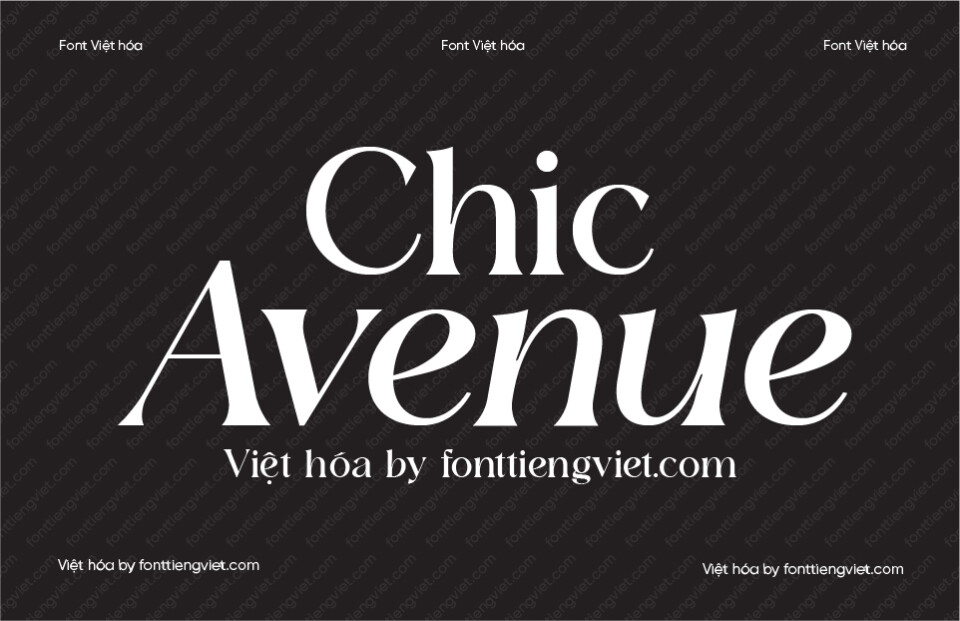
Font Việt hóa 1FTV VIP Chic Avenue
Font Việt hóa 1FTV VIP Chic Avenue – Bộ Font Chữ Sang Trọng Cho Thiết Kế Thời Thượng
Trong thế giới đồ họa hiện đại, việc tìm kiếm một bộ Font Việt hóa 1FTV VIP Chic Avenue hoàn chỉnh và tinh tế là nhu cầu thiết yếu của các nhà thiết kế. Đây là một phông chữ mang phong cách Serif cổ điển nhưng lại pha trộn hơi thở của sự sang trọng và đẳng cấp. Nếu bạn đang thực hiện các dự án liên quan đến thời trang, tạp chí cao cấp hoặc các thiệp mời sự kiện quan trọng, bộ Font Miễn Phí này chắc chắn sẽ là lựa chọn không thể bỏ qua. Với đường nét thanh mảnh kết hợp cùng các góc cạnh sắc sảo, bộ chữ này tạo nên một diện mạo chuyên nghiệp và đầy sức hút cho bất kỳ ấn phẩm nào. Việc tối ưu hóa tiếng Việt giúp người dùng không còn lo lắng về lỗi hiển thị dấu, từ đó tập trung hoàn toàn vào việc sáng tạo nghệ thuật một cách mượt mà nhất.
Đặc điểm nổi bật của Font Việt hóa 1FTV VIP Chic Avenue
Mỗi bộ phông chữ đều mang trong mình một câu chuyện và phong cách riêng biệt. Đối với bộ phông này, sự tỉ mỉ trong từng đường nét chính là điểm nhấn giúp nó nổi bật giữa hàng ngàn phông chữ khác trên thị trường hiện nay.
Sự kết hợp hoàn hảo giữa cổ điển và hiện đại
Bộ Font Việt hóa 1FTV VIP Chic Avenue sở hữu cấu trúc chữ Serif đặc trưng với các chân chữ rõ ràng nhưng không quá cứng nhắc. Điều này giúp văn bản giữ được sự trang trọng cần thiết mà vẫn mang lại cảm giác nhẹ nhàng, bay bổng. Các ký tự được thiết kế với độ tương phản cao giữa nét thanh và nét đậm, tạo ra hiệu ứng thị giác mạnh mẽ, đặc biệt hiệu quả khi sử dụng làm tiêu đề cho các bìa sách hoặc poster quảng cáo.
Khả năng tương thích và Việt hóa chuẩn xác
Một trong những ưu điểm lớn nhất của bộ phông này chính là quá trình Việt hóa kỹ lưỡng. Các dấu câu tiếng Việt được đặt ở vị trí cân đối, không làm thay đổi cấu trúc gốc của bộ chữ. Nhờ vậy, người dùng có thể sử dụng Font Việt hóa 1FTV VIP Chic Avenue cho cả đoạn văn bản dài mà vẫn đảm bảo tính thẩm mỹ và dễ đọc. Phông chữ này hỗ trợ tốt trên nhiều phần mềm thiết kế phổ biến hiện nay như Adobe Photoshop, Illustrator hay Canva, giúp quy trình làm việc trở nên thuận tiện hơn bao giờ hết.
Ứng dụng thực tế của phông chữ trong đời sống
Không chỉ giới hạn trong lĩnh vực thiết kế chuyên nghiệp, bộ phông chữ này còn len lỏi vào nhiều khía cạnh khác nhau của đời sống nhờ tính ứng dụng cao và vẻ đẹp vượt thời gian mà nó mang lại.
Thiết kế thương hiệu và bao bì sản phẩm
Với vẻ ngoài sang chảnh, phông chữ này thường được các nhãn hàng mỹ phẩm, trang sức và nước hoa ưu tiên lựa chọn. Khi in ấn trên bao bì, nó tạo cảm giác cao cấp và tin cậy cho khách hàng. Ngoài ra, việc sử dụng phông chữ này cho logo thương hiệu cũng giúp định vị phong cách quý phái, khác biệt hoàn toàn so với các đối thủ cạnh tranh trên thị trường.
Trang trí văn phòng phẩm và thiệp mời
Trong các trường học hoặc môi trường giáo dục, việc sử dụng các phông chữ đẹp mắt như Font Việt hóa 1FTV VIP Chic Avenue giúp các em học sinh có thêm cảm hứng học tập. Thầy cô giáo có thể dùng phông chữ này để thiết kế các mẫu giấy khen, thiệp chúc mừng hoặc trang trí bảng tin lớp học. Sự tinh tế của phông chữ giúp các nội dung truyền tải trở nên trang trọng và có sức nặng hơn đối với người tiếp nhận.